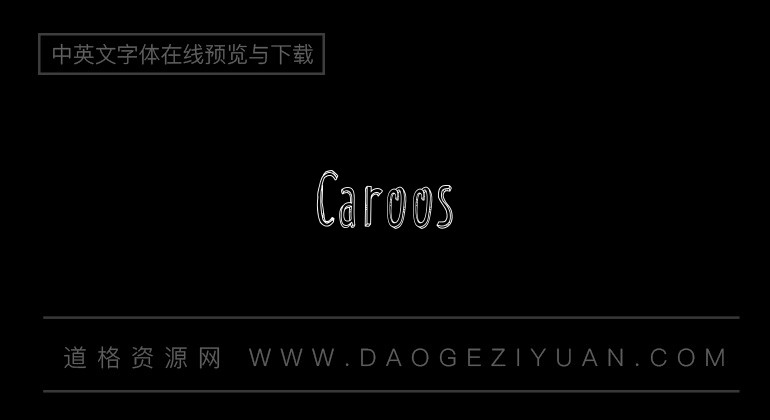
Caroos
Caraos 字体是一款新颖的极简主义字体,它拥有非常轻盈的线条,使得文字看起来更加清晰,而且它的细节也很精致,能够更好地帮助读者理解文字内容。它的字体结构更加紧凑,使得文字能够更好地表达出来,而且它的字体也更加简洁,使得文字看起来更加简洁大方。此外,Caraos字体也具有良好的可读性,它的字体结构能够更好地帮助读者更容易理解文字内容。
Caroos是一款非常不错的手写艺术字体,具有很好的视觉感,适合于文化类的宣传设计、商业类品牌的广告和产品包装设计以及个性化文字排版等较多场景。